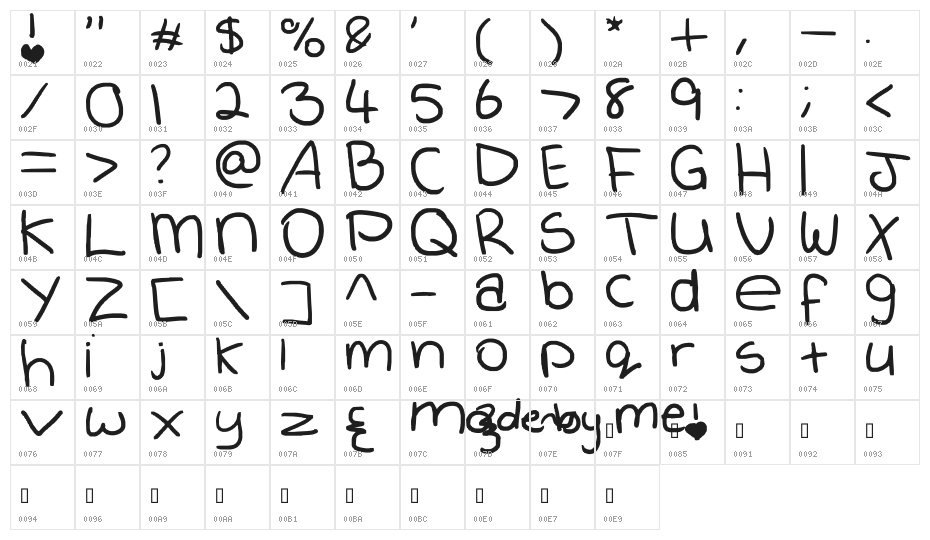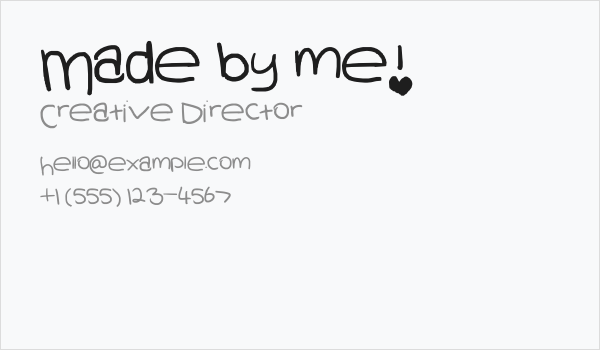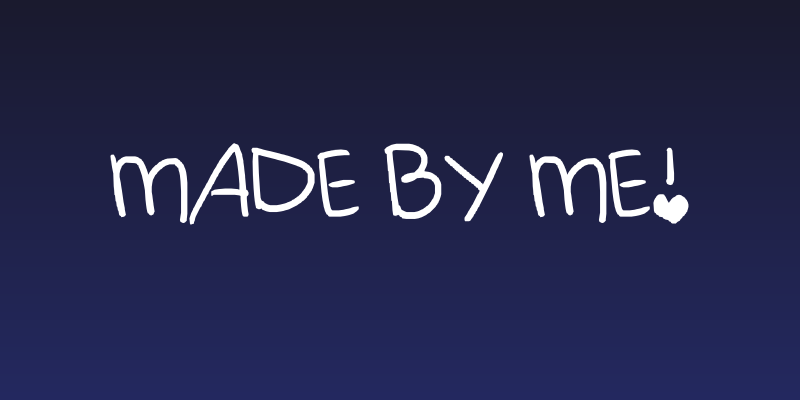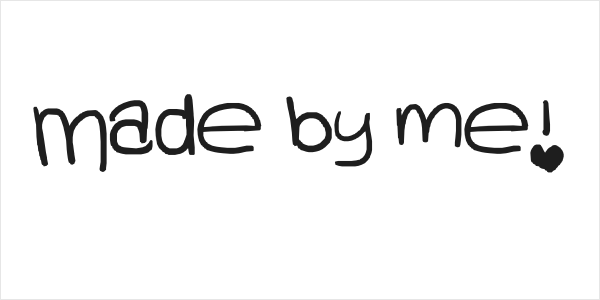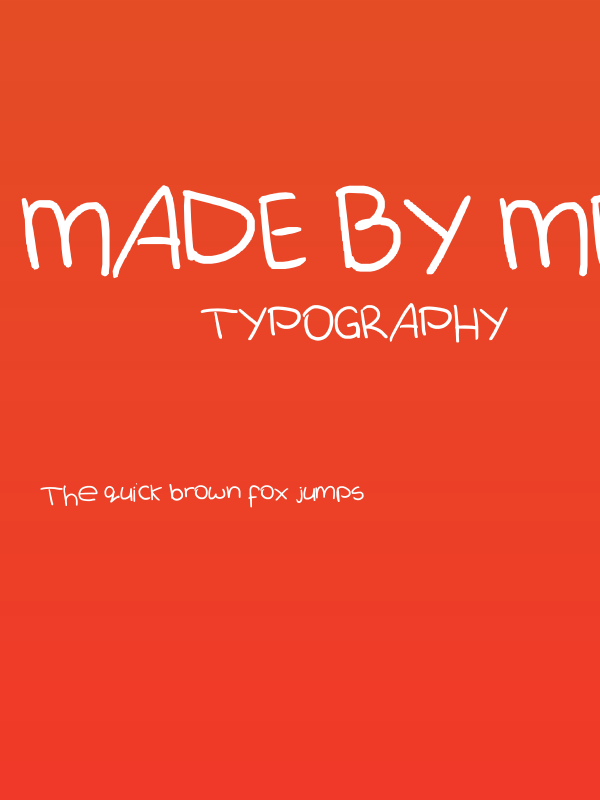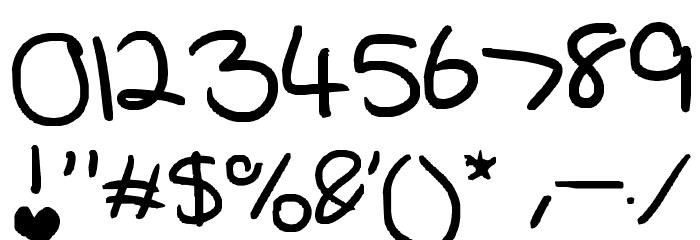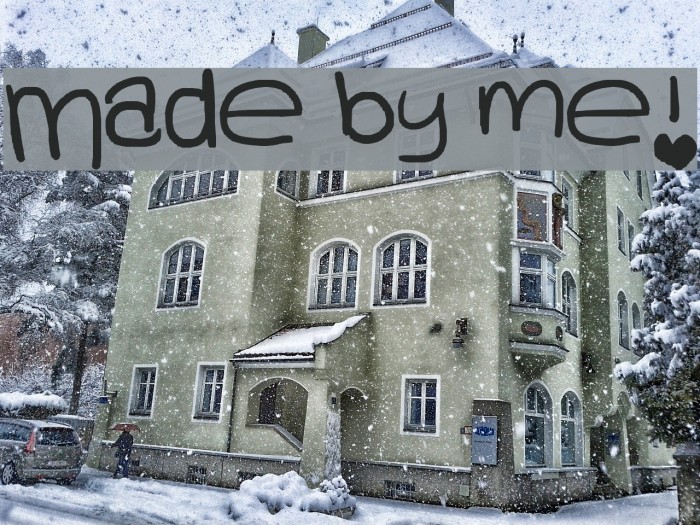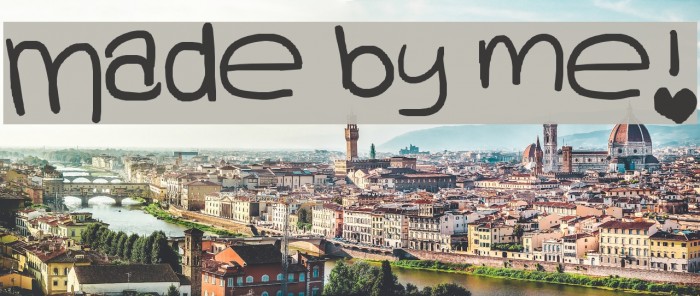
Made by me! Font
| Stile generale | Casual |
| Caso d'uso | Headlines, Informal text, Creative projects |
| Progetti proposti | Ideal for greeting cards, children's books, personal blogs, and creative projects that require a warm and informal touch. |